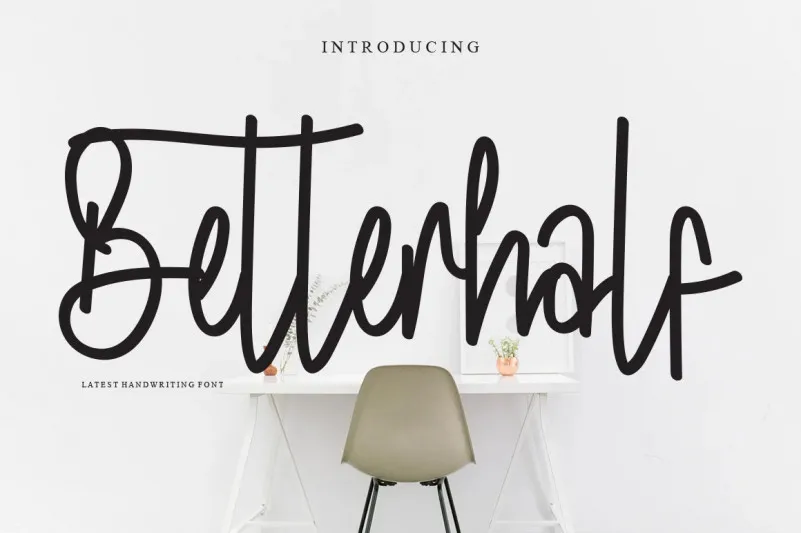
Betterhalf Font
Esta é uma fonte escrita à mão única e elegante. Ideal para qualquer projeto que busque personalização, seja ela um convite de casamento, cartão de agradecimento, logomarca, cartaz de aniversário ou qualquer outra aplicação gráfica em que desejas dar um toque único e especial. Suas linhas suaves e detalhes cuidadosos fazem dela uma escolha perfeita para quando você quer expressar sua personalidade através do design. A fonte “Betterhalf” é especialmente adequada para estilos de design pessoais, como os convites de casamento que exigem um estilo único. Não é apenas para nomes e datas: ela abrange o mundo das cartas de agradecimento e até mesmo as personalizações em logotipos, tornando-a uma fonte versátil que pode ser usada em qualquer projeto onde você deseja dar um toque pessoal à sua marca ou arte.